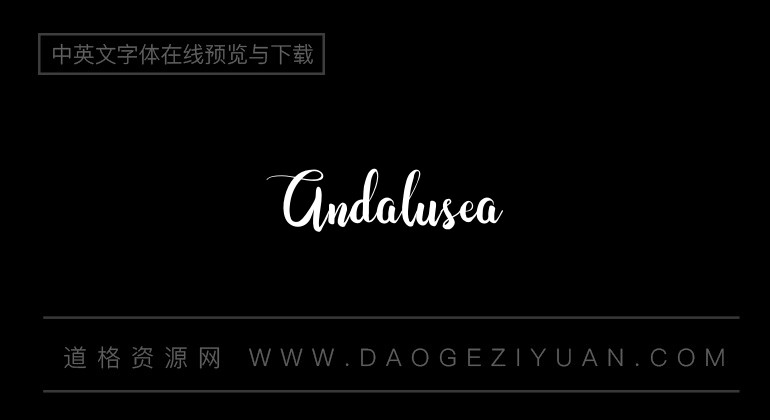
Andalusea 是一款现代简约风格的字体,由西班牙设计师Juanjo Lopez创作。它拥有一种温暖而柔和的氛围,使用它可以在您的设计中添加一些温暖和舒适的气息。Andalusea字体有着明显的西班牙风格,它的特点是细腻的线条,圆润的字形,以及细节精致的结构。它可以用于各种应用,如标志,海报,书籍,网站,应用程序等等。它可以帮助您的设计变得更加精致,更有趣,更有吸引力。内容介绍
Andalusea是一款非常不错的手写艺术字体,具有很好的视觉感,适合于文化类的宣传设计、商业类品牌的广告和产品包装设计以及个性化文字排版等较多场景。